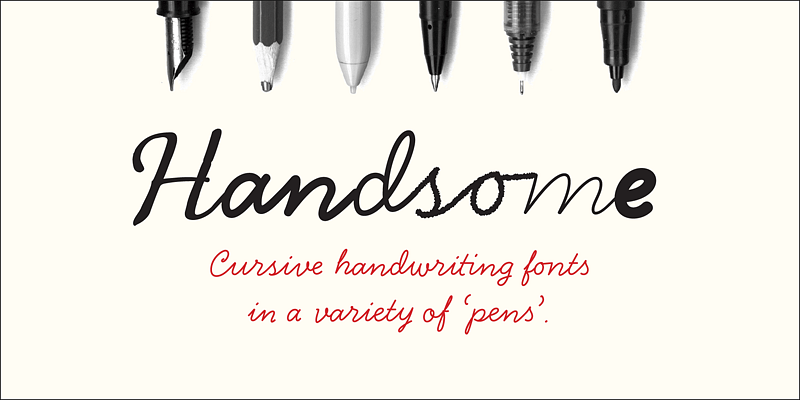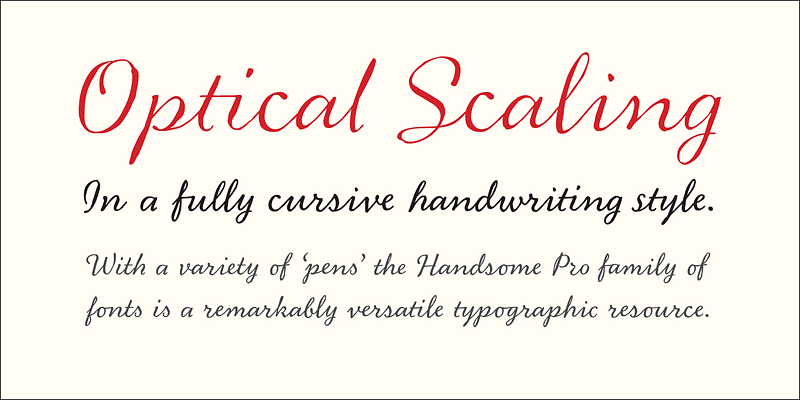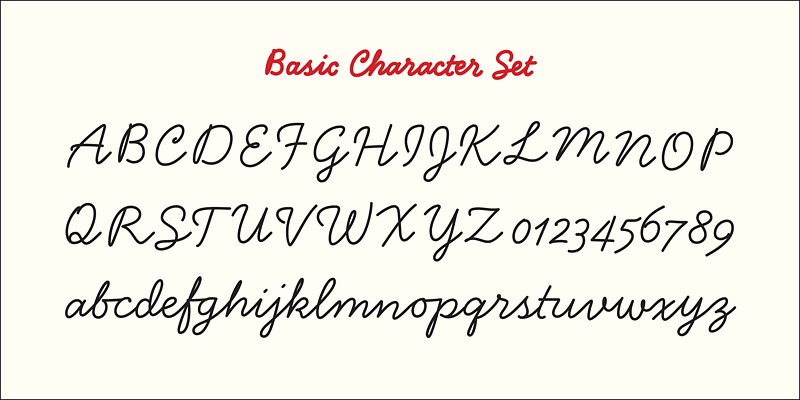
Die digitale Schrift als biomimetische Software, die eine Roboterschrift herstellt, die ihre Künstlichkeit hinter einer wechselnden Besetzung von Buchstabenalternativen verbirgt. Indem Handsome die verbindenden Regeln der Schreibschrift nachahmt, hält er der Stiftkultur einen Spiegel vor und enthüllt eine Affinität zwischen der systematischen Struktur formaler Schriftsysteme und der programmierten Logik fortschrittlicher digitaler Typografie.